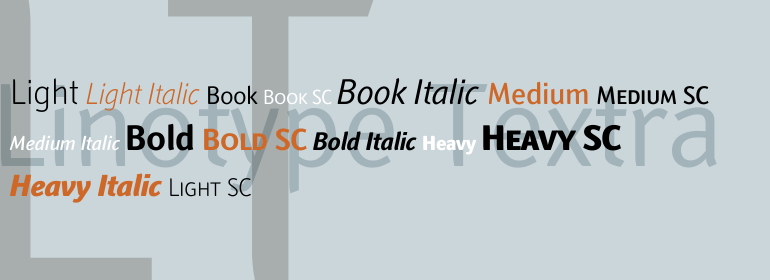
Linotype Textra™
Linotype Textra™,这款字体结构工整、笔画清晰,兼顾美观与易读性,适用于标题、正文、海报、包装、LOGO 等多种场景。字形优雅稳定,风格百搭耐看,适配日常排版与创意设计,让文字呈现更舒适、更具质感。Linotype Textra™一笔一画,皆是细节,以均衡的比例、流畅的线条打造舒适视觉体验,字形端正大气,风格简约现代。无论是商业设计、品牌宣传还是日常排版,都能轻松驾驭,让文字更有格调与力量。Linotype Textra™字体下载。
字体品牌: Linotype(Monotype) 设计师:Schuss,Jochen; Herz,Jörg 字体分类:无衬线体 字体属性:外文 字符集:Unicode 发布时间: 2018